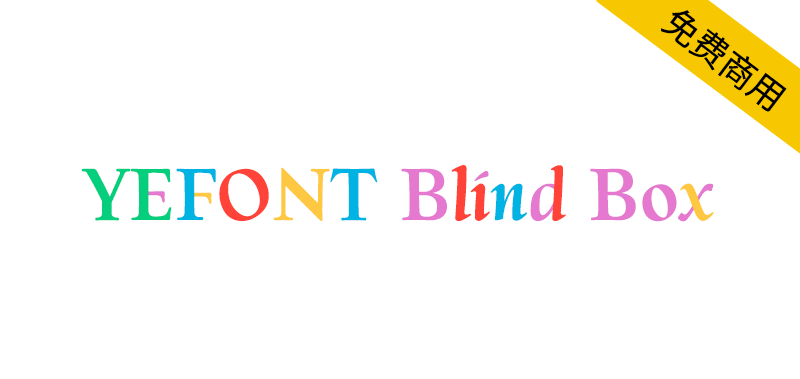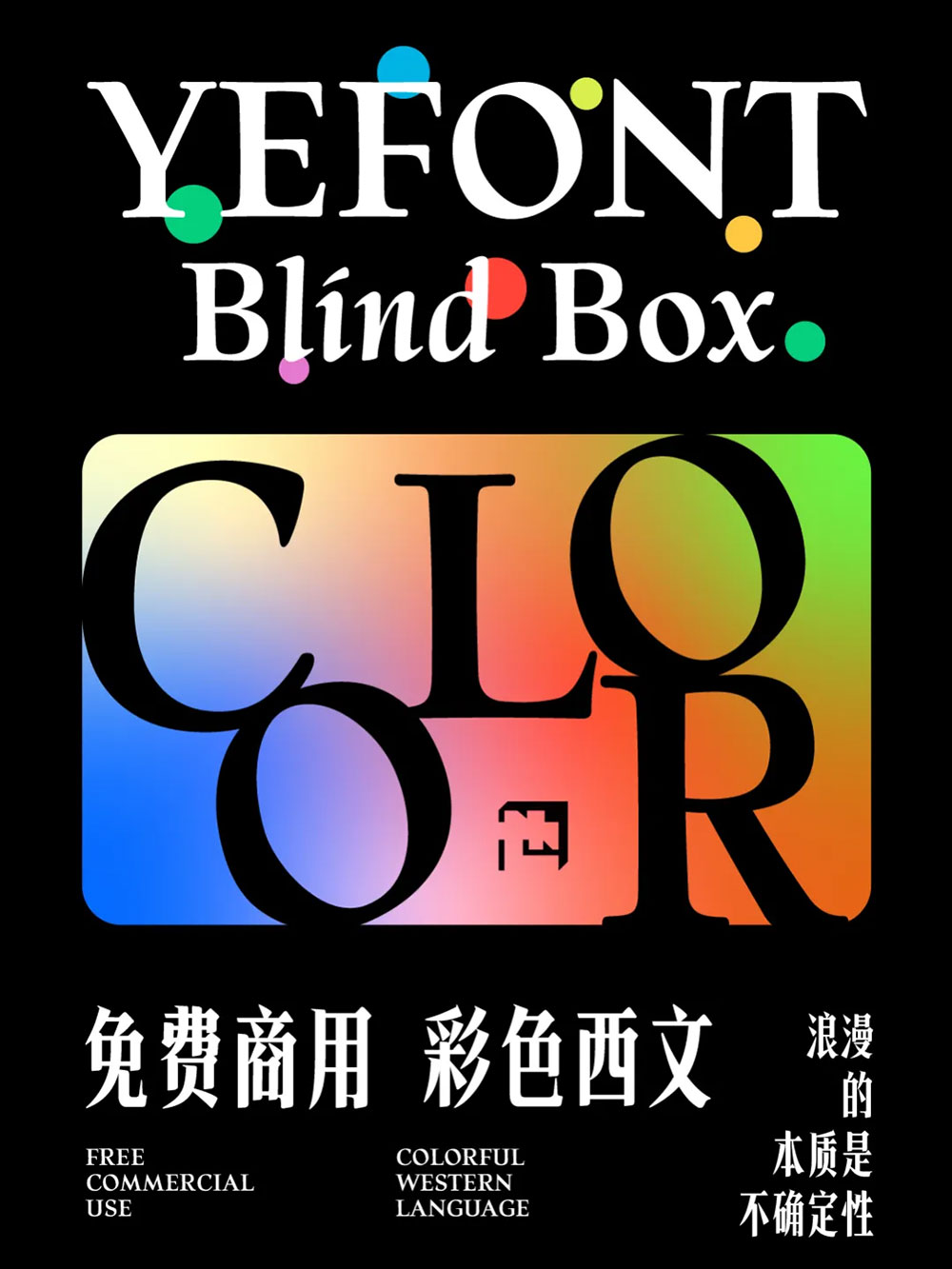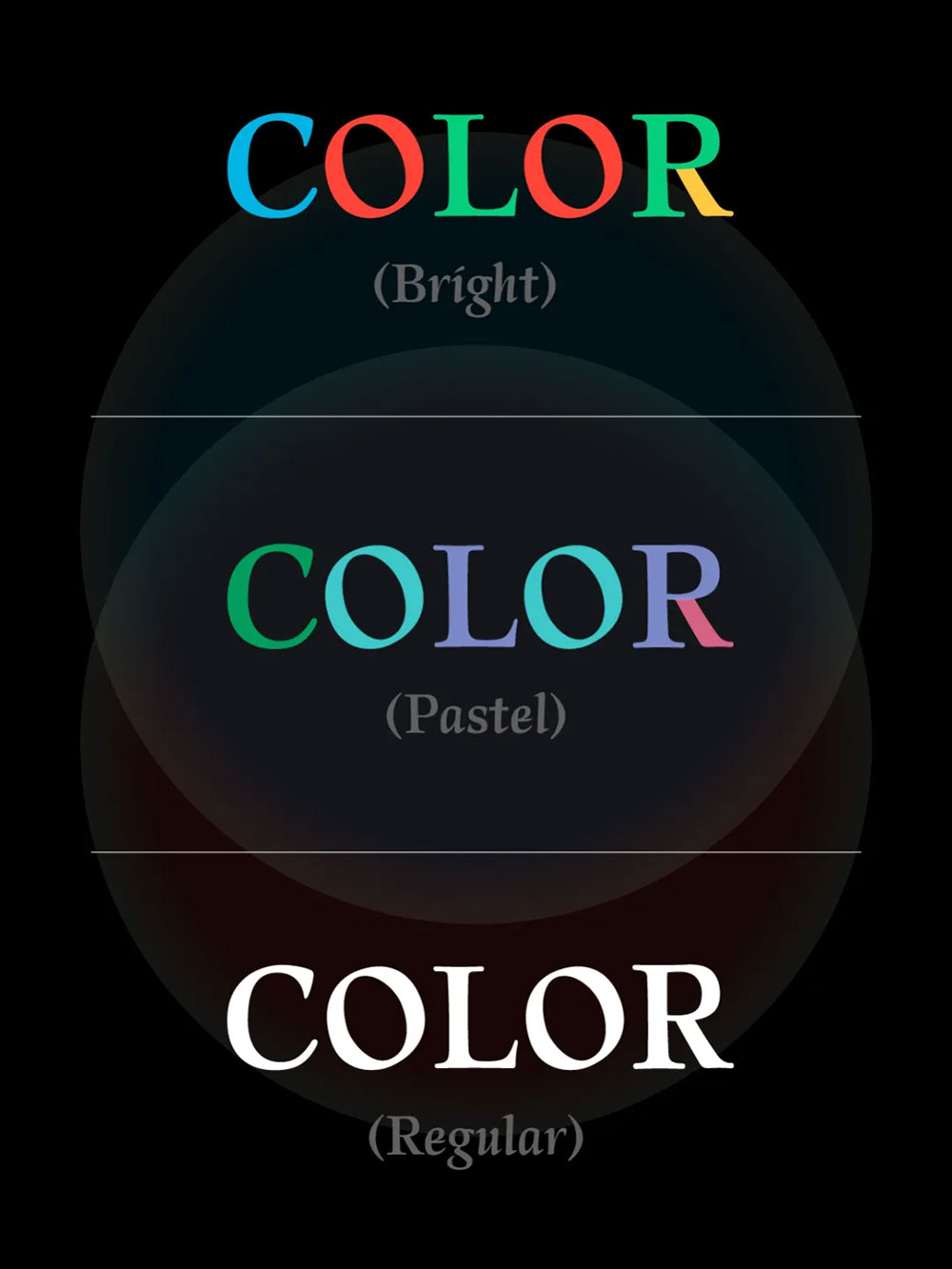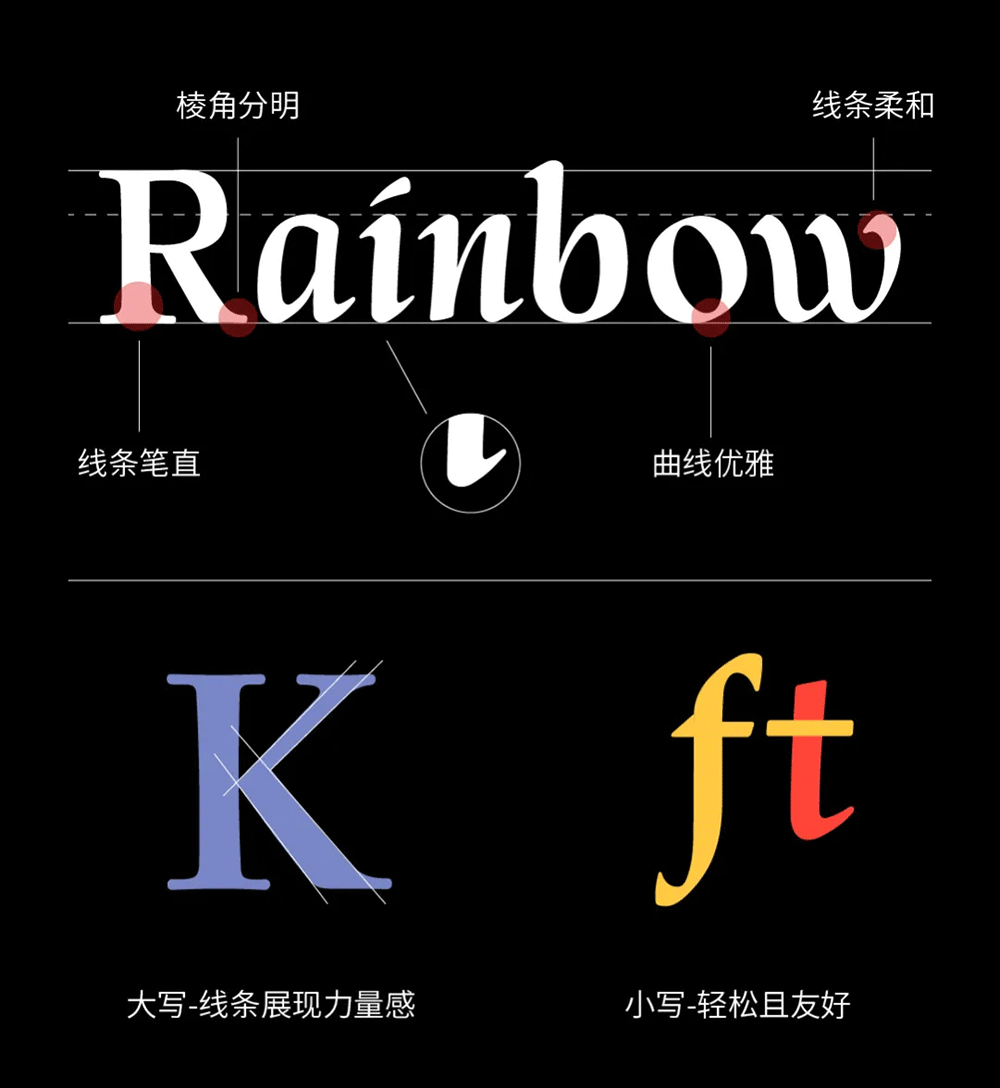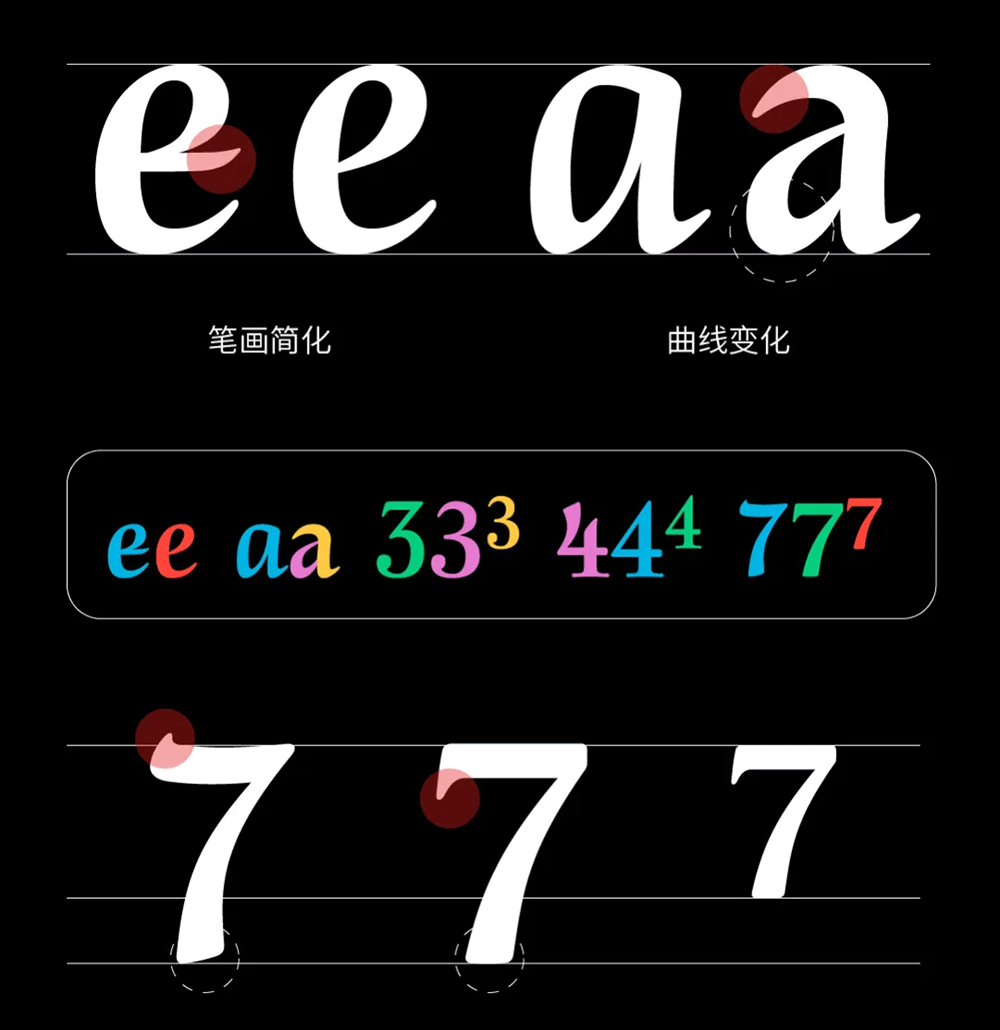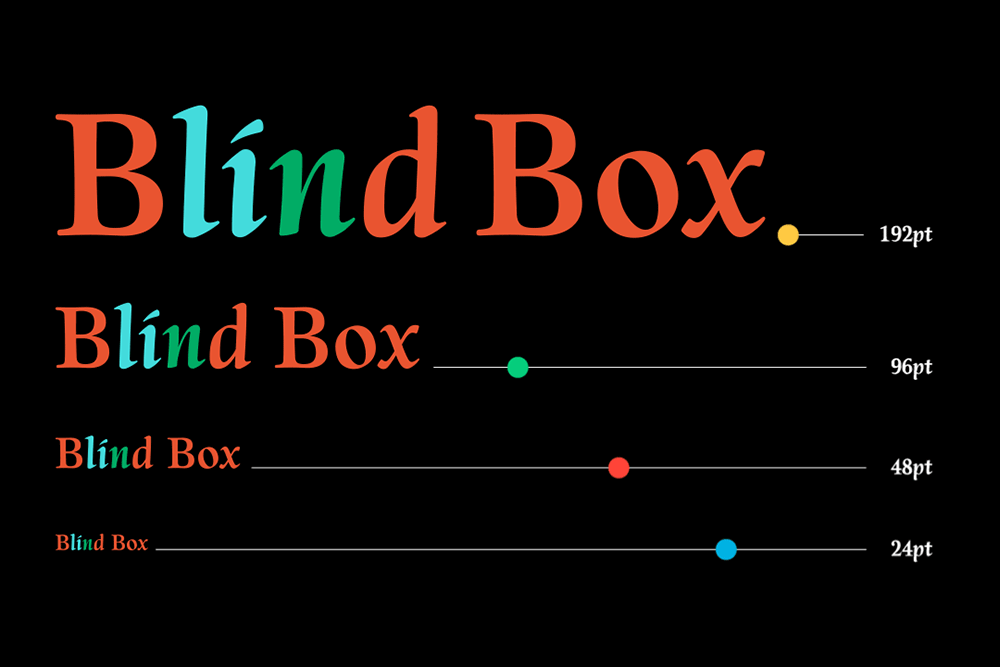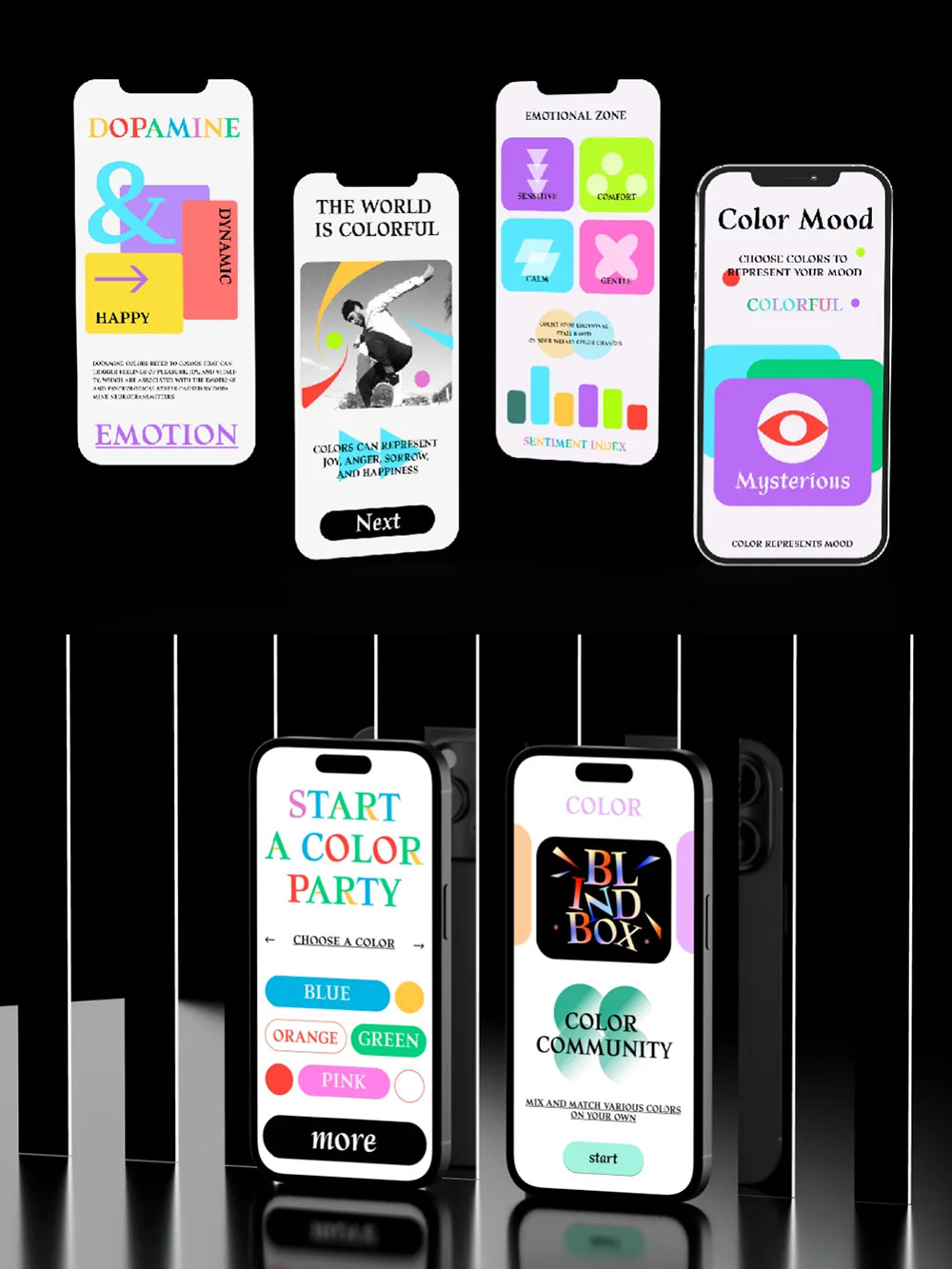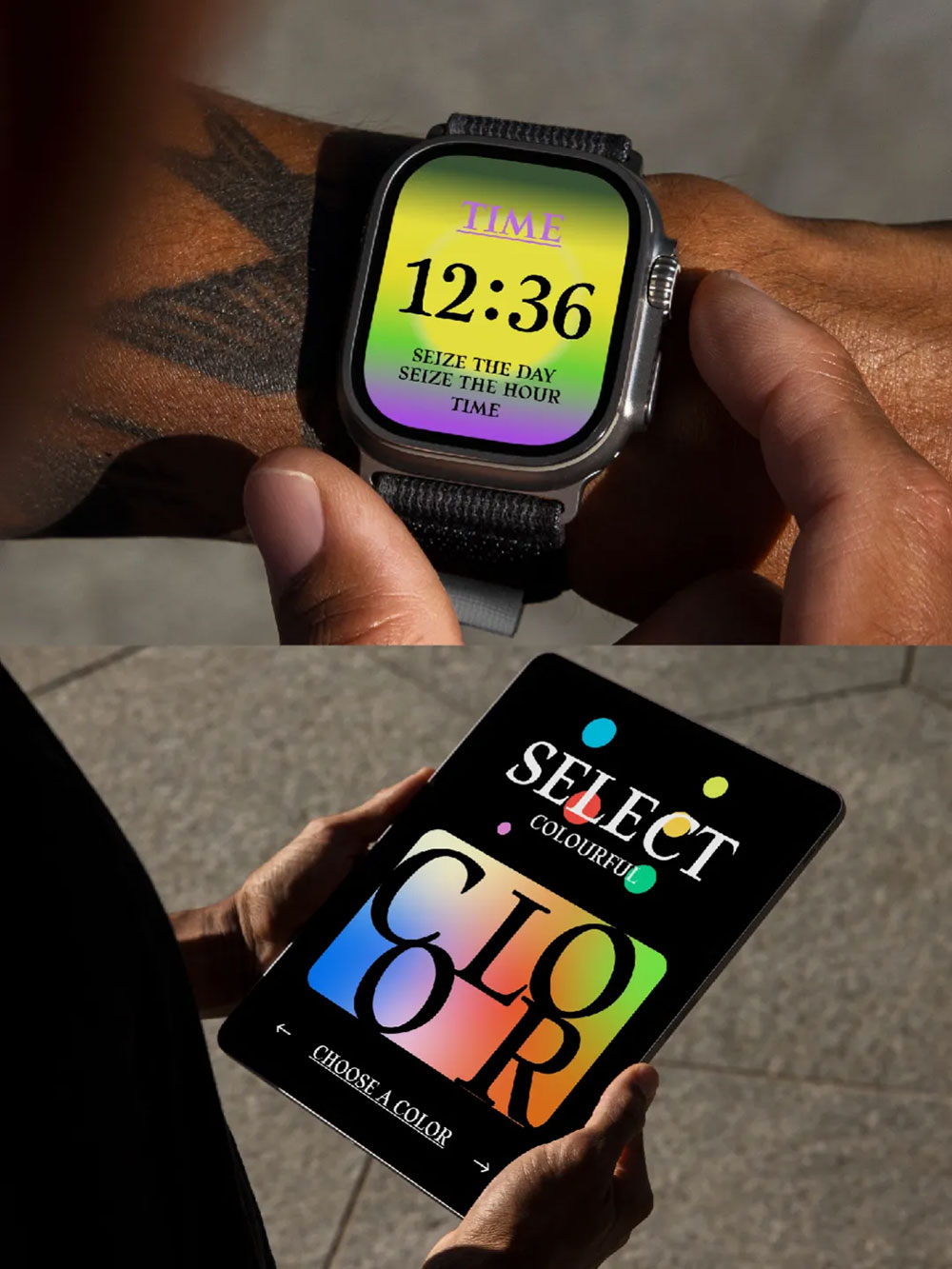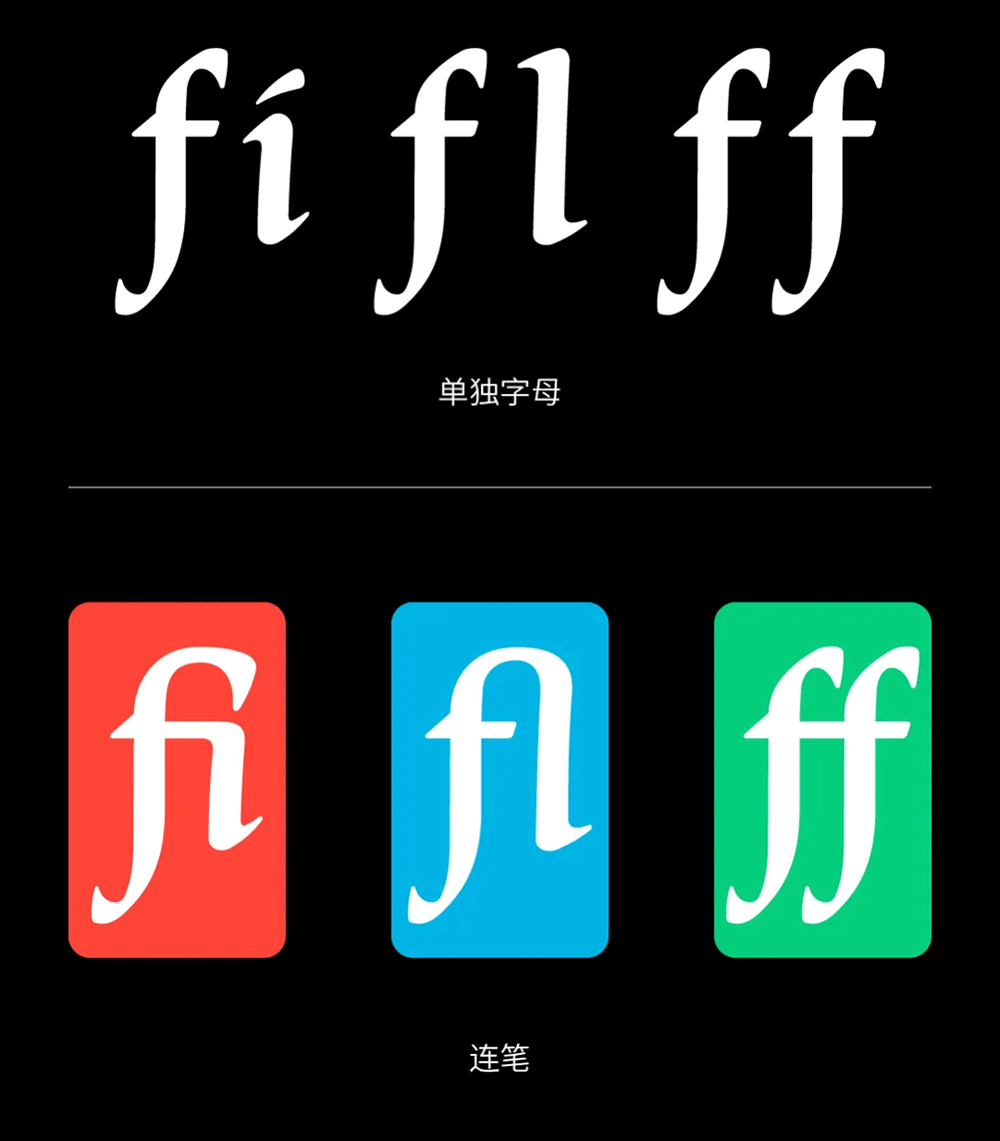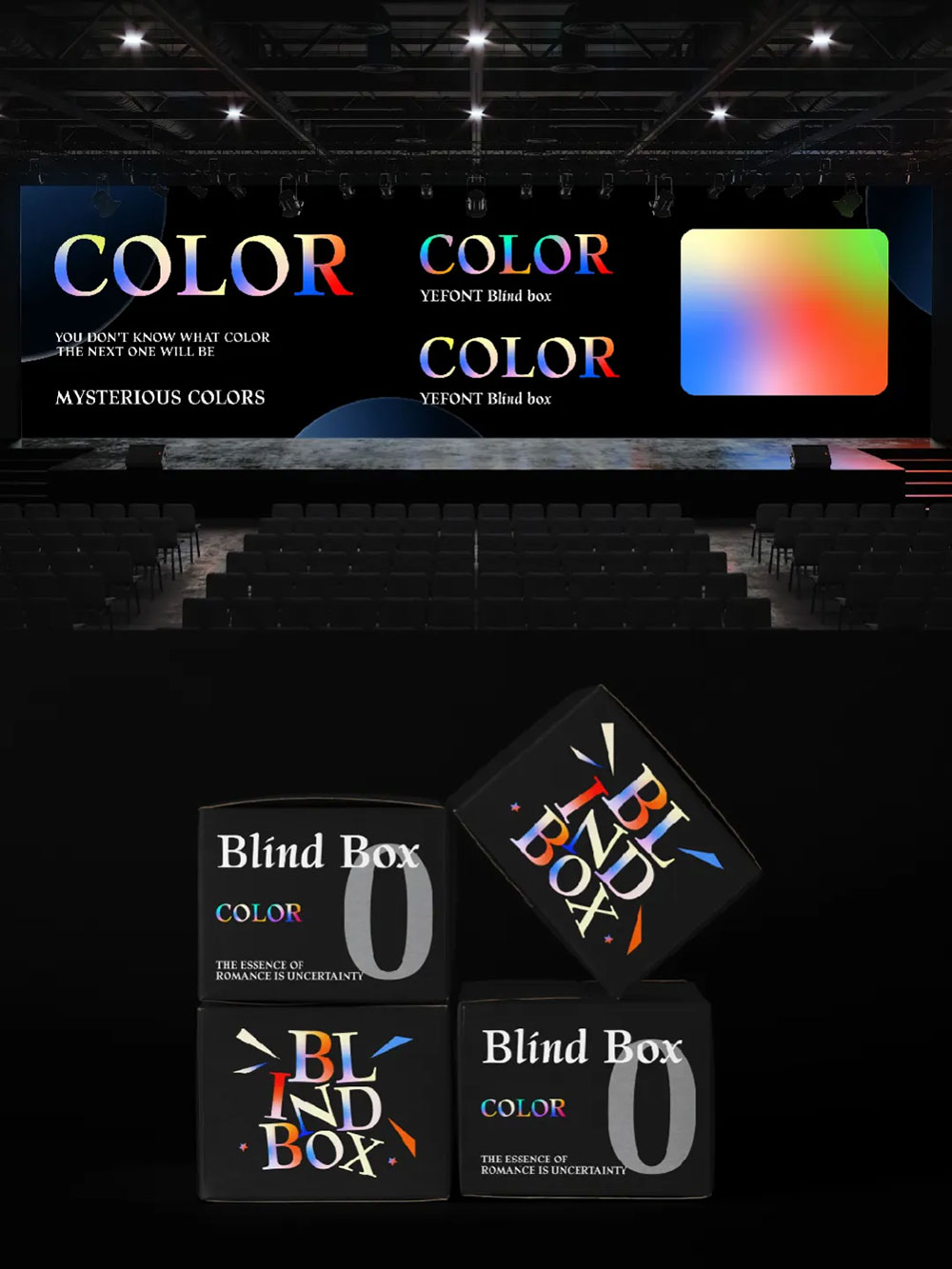
设计师们,还在为寻找免费又独特的西文字体发愁吗?也字工厂重磅推出YEFONT Blind西文字体,第三款免费商用字库!提供春季活泼色和秋季柔和色彩色版本,外加常规选择,巧妙融合复古曲线与现代几何造型,视觉独特易读。支持OpenType-SVG彩色格式,兼容主流软件;部分字母多字型替换和连笔设计,让排版自由多变。适用于品牌标识、广告海报、UI设计等多元场景,激发无限创意。立即下载,打造你的年轻化设计作品!
YEFONT Blind Box 是由「也字工厂」专业设计师团队精心打造的一款彩色西文字体,也是【也字出品】栏目正式推出的第三款免费商用字库。这款字体将会提供两个彩色版本以及一个常规版本,其中,彩色版本分为明亮活泼的春季色系和低沉柔和的秋季色系。
字体特征 : 复古与现代的结合,在Blind Box的创意阶段,我们倾向于关注字体的实际应用效果,一是在设计中能体现品牌的年轻化和独特性,二是字体的本质即易读性,识别度高。于是,现代欧美平面设计的多彩艺术风格,成为了我们的首选。
YEFONT Blind Box 在字母的造型设计上,我们结合了几何造型与传统西文字母的优雅曲线,视觉上简明独特,又能适应多元文化背景的设计需求。
其次,部分字母和数字提供了多字型的替换,在标题和正文的排版中拥有更丰富的适应性和表现力,让设计师能根据不同的场景或需求自由创作。部分字母提供多字型替换,部分字母提供“连笔”设计。
这套字库支持OpenType-SVG 彩色字体格式,兼容 Adobe Illustrator、Photoshop 等软件(Ps:本款字体的彩色效果,目前仅限部分软件使用;更多软件正在紧锣密鼓地开发中,敬请期待!)。矢量彩色设计,放大后依然清晰可见。
应用效果 :无限的创造潜力,融合了现代欧美艺术中的几何造型与衬线体自带的优雅气质,为YEFONT Blind Box塑造出一股年轻活力的特质,适用于品牌标识、广告、海报以及UI设计等多重领域。